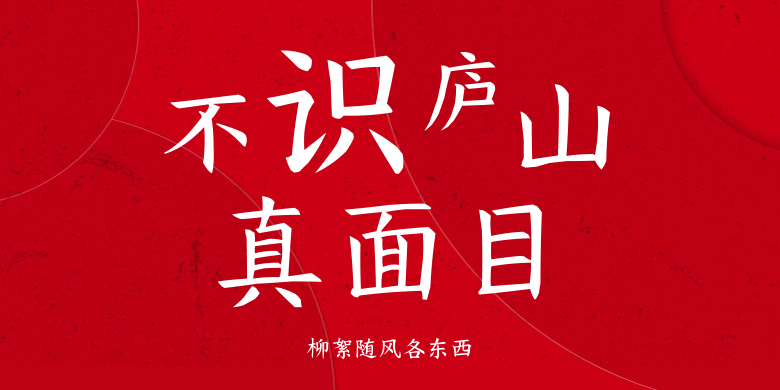
柳絮随风各东西
柳絮随风各东西,这款字体结构工整、笔画清晰,兼顾美观与易读性,适用于标题、正文、海报、包装、LOGO 等多种场景。字形优雅稳定,风格百搭耐看,适配日常排版与创意设计,让文字呈现更舒适、更具质感。柳絮随风各东西一笔一画,皆是细节,以均衡的比例、流畅的线条打造舒适视觉体验,字形端正大气,风格简约现代。无论是商业设计、品牌宣传还是日常排版,都能轻松驾驭,让文字更有格调与力量。柳絮随风各东西字体下载。